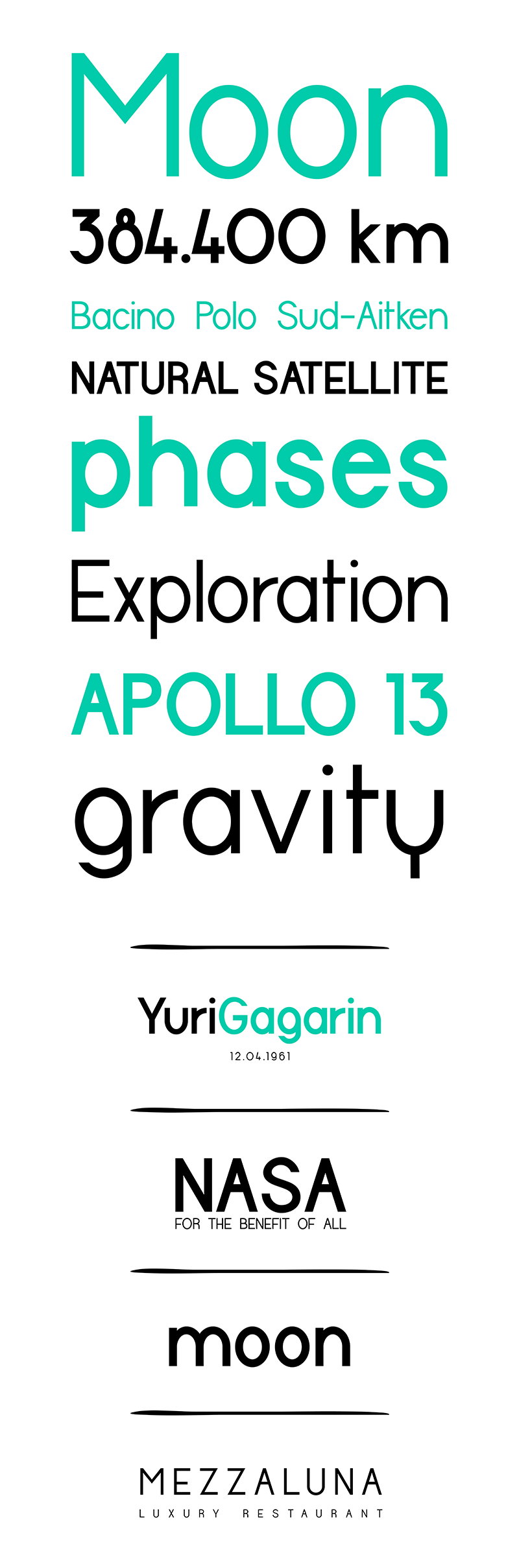
A Halfmoon é uma fonte Geométrica Sans Serif criada por Monofonts como uma evolução da Opificio. Compara-se com sua antecessora, destacando-se pela presença de formas elípticas que a distinguem pelo fácil leitura, ao mesmo tempo que suas linhas simples a tornam uma excelente escolha para fontes de texto. Como mencionado por Adrian Frutiger: “Se lembrar do formato de seu garfo no jantar, tem que ser o formato errado. O garfo e as letras são ferramentas; um para coletar alimento da tigela, o outro para coletar informação do papel… Quando é uma boa design, o leitor deve se sentir confortável, pois a letra é tanto banal quanto bela.” Essa característica permite que a Halfmoon seja usada não apenas em gráficos digitais, mas também em textos profissionais e cotidianos.